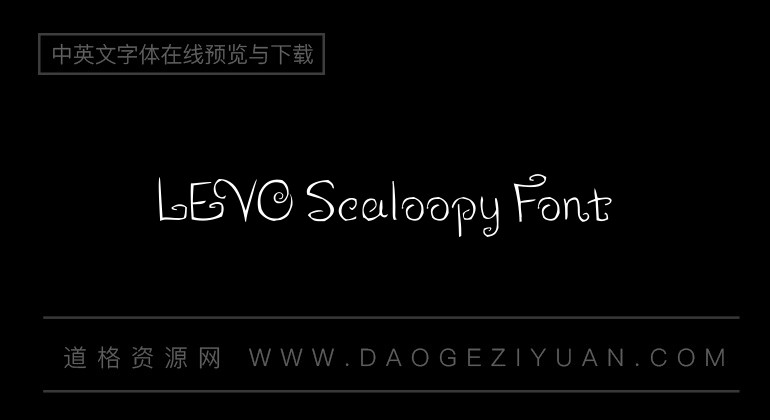
LEVO Scaloopy Font
LEVO Scaloopy Font是一种手写风格的字体,看起来趣味和活泼。这种字体由字母和数字组成,每个字符都具有独特的风格和个性。 该字体的特点是线条弯曲、斜向和交错,似乎是手绘而成,这使得它看起来非常有趣和新颖,适合用于设计海报、卡片、标志以及其他需要吸引人目光的文本上。 LEVO Scaloopy Font字体的设计者是来自意大利的Gianluca Giacoppo,他在创建这种字体时受到自己的手写和插画风格的启发,所以该字体的风格非常独特。
LEVO Scaloopy Font是一款非常不错的手写艺术字体,具有很好的视觉感,适合于文化类的宣传设计、商业类品牌的广告和产品包装设计以及个性化文字排版等较多场景。